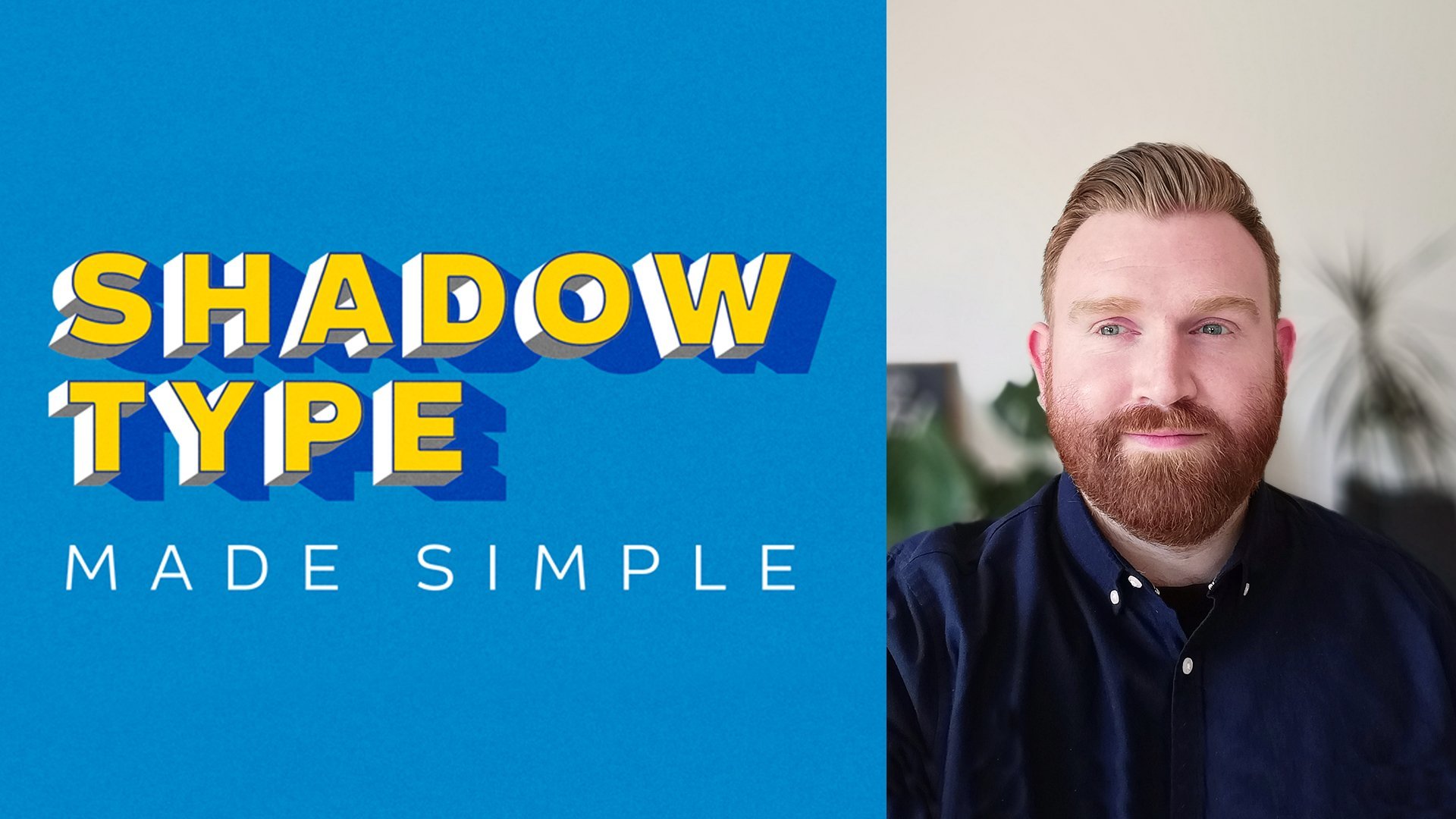
Tipografía con sombra en Adobe Illustrator simplificada
Introducción
Cómo hacer ideas en miniatura
Cómo seleccionar una paleta de colores de masal
Fuente de sombra y luz
Crear tipo de 3D
¿Dónde estamos ahora?
Retoques finales
Crea una pieza de lettering en 3D de tu cita favorita.
Una descripción del proyecto de clase:
• Trucos para hacer el dibujo y el diseño de tipografía fácil
• ¿Cómo se nail la selección de tipo?
• Aprende a crear un impacto con el color
• ¿Cómo elegir las mejores combinaciones de tipo?
• ¿Cómo añadir profundidad y interés a tu trabajo?
• ¿Qué son esos toques finales que hacen un zing?
1. Introducción: Hola, Mi nombre es Russell. Soy diseñadora freelance. Trabajo en Londres y alrededores para clientes grandes y pequeños. Tengo casi 10 años de experiencia trabajando en una variedad de proyectos que van desde cualquier cosa como palabra de identidad de marca hasta conferencias personalizadas para marcas de gran nombre. Durante este tiempo, no tengo que trabajar de manera eficiente e inteligente a Craig. Qué espantoso llamativo. A lo largo de esta clase, mis consejos de profesor tienen que puntar en promedio laico. Es como golpear lo horribles que las paletas de colores clavan esas combinaciones de tipos y cómo agregar a la deuda a tu trabajo. Bueno, entonces generalmente habilidades para crear tu propio impacto, por favor. Este pasado implica colección La habilidad se puede aplicar fácilmente a otras áreas de diseño o conferencia desde cualquier cosa como consejos sobre cómo diseñar conferencias. Crear sus propias pautas para financiar la selección o incluso seleccionar paleta de colores. Crean para golpear a la obra. Aprendes esos atajos de mano que puedes usar en Illustrator en photoshop al final de su corazón para poder sacar efectivamente una pieza de respuesta única de conferencia porque a partir de combinaciones sabes crear impacto. Cualquier preocupación, directorio o diseño que se le añada detalles extra. Esta clase tendrá apenas arriba tu juego, solo terminando y cruzando o qué 2. Cómo hacer ideas en miniatura: cosa muy rápida y fácil de hacer lo que tiempo. Por lo que sólo dibujamos nuestros lineamientos. No enviarlo como fondo organizado. Pero te mantendrá en un asustado no en la ciudad te salvará. Genial. Entonces te quitas las cerraduras aquí. De ninguna manera. Sabemos que nuestra palabra está colgando. De acuerdo, Punta rápida para que cualquier cosa sea re letras. Yo estaba rompiendo las ballenas en bloques visuales. Imagínese, como un número de rompecabezas que así sé que cuatro está en Hang dos es inning. Y en este cinco ahí dentro y eso solo te ayuda a planear. Aquí vas a romper 20 comentarios, trabajando en los frentes y esas cosas, ya sabes, espacios y todo lo que va a funcionar. Genial. Tomémoslo en ritmos realmente rápidos. A lo mejor algo en ángulo nos va a funcionar. Para que conozcas estas las que queremos destacar y en va a haber un sub minúsculo poco en algún lugar ahí. Tres noches que eso es en términos de prudencia pueden ser una, dos y tres. Vamos a tomarlo. Tal vez un competidor en un ángulo de Gricar's y hang podría estar disparando a través de la página en Podría estar en unos círculos pequeños y ellos y sus podrían seguir ese yendo a la derecha Teoh ángulo. Todo así se va a enderezar. Está bien, genial. A lo mejor eso es intentarlo. Me pregunto un truco de ángulo. Está pasando por el tablero Delgadez o lo que vemos en esa forma los ángulos siguen siendo los mismos marcos. Y simplemente no lo hicimos muy rápido y quedándonos en la ciudad. Sí, encantadora. Entonces sabemos entonces que fueron sombras. Podría ser que esta es una bonita sección transversal hay cosas diferentes pasando. Y te imaginas las sombras a tu cruz derecha diciendo, Eso es lindo. Tienes a mi serpiente al espacio lleno de pareja que le decimos antecedentes que sería una especie de convertirse en una Ya sabes lo que realmente está mal? Tan solo llévala a la siguiente etapa. Nosotros solo un poco más de lápiz labial en ella. Eres bueno. Y esto pensar a través de los chicos que hacen es un poco más agradable porque trabajo en los ángulos. Pero estabas en el distrito. Llévame a ver No. Entonces voy mano tensando que habrá fuera escaleras tipo de edad una vez un marciano dentro ahí. Por lo que probablemente se sentará en cualquier dispositivo que utilicemos para que diga realmente agradable manera rápida, fácil tus ideas sobre la edad, olvidando gallinero en lápices en fotos, lápices cortos en Australia, colores formas. Si auto idea realmente limpia llena de artesanía en Charles, es una muy bonita y esto acaba de finalizarse lo que ponemos en página. Después llevamos esto a las televisiones al instructor. Miramos los fondos y vemos qué podemos tomar en cuanto a que son. Creo que esto es realmente, bueno, genial. 3. Cómo seleccionar una paleta de colores de masal: El paleta de colores es una de las partes más importantes de un diseño que le crea que eres capaz de escoger un combo de colores que realmente, realmente aparece. Tu objetivo principal es crear contraste en tu paladar y pieza de trabajo. opuestos claros y oscuros y de color en la rueda de color son tus mejores apuestas por igual. Los colores de Mood boarding realmente pueden obtener tu inspiración. Gary. A partir de esto puedes dejar caer los colores y empezar a crear un impacto realmente conceptual para la paleta de colores. De acuerdo, entonces, ¿dónde encuentras el color? Hay algunos grandes recursos alrededor, y creo que como diseñadora, realmente deberías estar esforzándome con materiales impresos. Este es un gran tipo de sombra de libro. Es brisa Filadelfia y Stephen. Helen es una gran colección fuera de tipo increíble de todo el mundo que personalmente y juntan. Te viniste sitios como ceniza virgen. Es muy bueno para inspirar paletas de colores, y realmente podrías sacar de las imágenes usando que lo dejo caer o para ti y lo llevo Illustrator o Photoshopped para hablar realmente genial. Imágenes de Teoh para tableros de humor Bendice. Mira ahora en un así vamos a través de la página para adobe color. puedes ver que tienes diferentes opciones para ir por las que pasamos ahora, tonos compuestos complementarios y personalizados, y es una gran herramienta en. ¿ Acabas de arrastrar por ahí? Este círculo aquí solo para jugar y seleccionar los colores de las joyas es realmente es de extremo abierto. Ahí tienes los colores hexagonales, lo cual es increíble de sacar. Puedes individualmente, bebé lo enorme de cada color que puedes establecer diferentes colores es de colores basados, lo cual es increíble hasta que quieres una base alrededor del auto y comienzas a probar nuestro monocromático que incluso puedes explorar. Y aquí es donde el color de Adobe realmente entra en el suyo. La gente no puede volar las paletas de colores, y automáticamente dice: ¿Es a partir de imágenes que se están subiendo? Y es una forma tan inspiradora de dibujar color de una comunidad incluso puede ver tendencias, y donde eso está alineado en la moda o diseño gráfico o ilustración. Es increíble ver cómo la gente está usando colores en diferentes industrias. Probablemente airearía del lado de la precaución con esto, y usted sólo utiliza su inspiración, explorar y crear van a estar donde realmente se puede cultura y crear esas paletas de colores allí fuertes en su trabajo. Aún mejor, aquí tienes opciones para sacar los colores en RGB c m y que HSV o lab, que es una herramienta tan asombrosa para tener al alcance de tus dedos. Por lo que recomendaría que los mares Aquí es donde deberías estar creando tu llamada al respecto porque es tan poderosa, tan fuerte. De acuerdo, ver que en este ejemplo, se puede ver que he sacado el tipo de la imagen del título para este auto encendido. He sacado los colores que utilicé en cada elemento individual, y ahí hay seis colores que van desde el fondo hasta los contornos de las sombras hasta los reflejos. El semáforo bajo. Se puede ver que he resaltado cada área y cada color diferente que he usado en una pieza de trabajo. Ahora pasemos al siguiente bit donde los he sacado en apenas una paleta de colores plana en círculos, solo para que veas el gran contraste en colores. Tienes tres tipos de blues, un color realmente fuerte, vibrante, un bonito cumplido, tu producto al blues para las sombras. A mí me gusta mucho destacar, y eso sólo va a escoger. ¿ En qué forma ayuda realmente? Gran impacto en tus letras. Esto se puede ver en nuestro siguiente bit, donde el tipo explota y se puede ver cómo se está componiendo esto en capas siempre diferentes . Y se puede ver cómo esos colores aquí realmente trabajan juntos para crear ese impacto para la paz de la letra sobre cuándo volverán juntos. Se puede ver que realmente conduce a casa la forma, la forma y cómo realmente funciona esa sombra. Difícil hacer que esta redacción realmente destaque. Forma de empezar con nuestros colores de seleccionados una bonita paleta de colores. Aquí puedes ver que hay un amplio plebeyos de despedida que tenemos apoyando verdes rojos de apoyo y realmente bonito color claro resaltado, lo cual es genial cuando les damos esperanza. Estos los greens y el meñique enorme están lo suficientemente lejos el uno del otro que van a bajar, lo cual es perfecto. Diga una nota rápida sobre el manejo del color. Y tal vez quieras seleccionar todo en uso, deshacerte de todo o de estos porque eso ha nacido. Entonces quieres agarrar que un selectivo lo bebió en ese seleccionado Arrástrelo en el mismo otra vez en esto es solo una ayuda realmente te maneja, Carlos, que nada va a estropear y quieres pasar y resbalarlos como globales. Ver, en lo que eso va a hacer es, um, Tesis dirá tu tocino en cualquier mal día. Cualquier color de cliente cambia cualquier último minuto se enmienda a los colores o decir tal vez necesitaban obras de arte en una hora, cualquier cosa por el estilo. Esto significará que debido a que es global, cambias las joyas de color en una vista previa, y cambiará en la cosa. Por lo que sólo hay que recordar que estos ahora están establecidos como thes colors se significa ahora que quieres sólo los colores. Estás bastante feliz. Tenemos el matiz o algo así. Simplemente puedes ajustarlo y ver lo rápido que fue eso. Qué asombrosamente rápido. Por lo que puedes cambiarlo para mentir Nombres azules regenerativos los oscuros. Puedes cambiarlo para ver em como un realmente es interminable en tu guardar. Tanto tiempo y esfuerzo acabamos de agilizar acciones inteligentes como esta siempre va a ahorrar mejor tiempo. Por lo que es genial tener esta licencia obvia para esos tiempos en los que sí consigues esos cambios de último minuto. Permanece su último minuto. Todos sabemos que sucede que esto te detendría poner en ese año. Por lo tanto, una forma realmente buena y práctica de controlar los colores y gestionar dentro del panel de muestreos utilizando herramientas globales en Adobe Illustrator. 4. Fuente de sombra y luz: legible ilumina a alguien que si no lo consigues del todo bien, destaca aquí. Se puede ver que he mostrado la fuente de luz para su pieza tipográfica desde las cartillas de título . Necesitas imaginar la luz que brilla hacia abajo desde la parte superior izquierda viniendo a través. Ponte al frente del tipo y rebotando, echando una sombra a los derechos del tipo. Imaginar el tipo como un objeto viviente estructural, respiratorio realmente ayuda a la hora de planear el sombreado en el color. En esta próxima luz, se pueden ver tres fuentes de luz y tres letras y cómo todas tienen efecto de manera diferente. Se puede utilizar esto como referencia. Cuando no lo afeité a tu pieza, podrás encontrar esto en la sección de recursos para su clase. Al pensar de dónde vendrá la fuente de luz, necesitas que Teoh también piense en qué ángulo se mostrará la profundidad. Se puede ver aquí que está usando el ángulo equivocado en la deuda equivocada en el ángulo de luz equivocado . Fuente no hace que el tipo pop o destaque Aquí. Se pueden ver tres ejemplos de tres fuentes de luz, pero también el ángulo sobre la muerte. Creo que este es un ejemplo realmente bueno del que se puede sacar porque se puede ver la fuente de luz no es la única parte en el espíritu del rompecabezas para el tipo de sombra. También es el ángulo que estás poniendo la profundidad de las letras que realmente puedes ver aquí. Esta es la mejor manera de hacerlo, porque si vas a hacer conferencias desde arriba, vas a ser tonta tener la profundidad,ya sabes, en un ángulo de refighting, porque de esta manera pones todo el foco en mensaje que será del tipo. 5. Crear tipo de 3D: tenemos nuestra divertida televisión que he presentado. ¿ God paletas de color nuestra justo para referencia Arriba allá en tenemos nuestro boceto en la parte superior izquierda del lado. Eso sería realmente útil, sólo de referencia de retroceso para alguna vez atascarse. Ahora la diversión que he usado una combinación de tamaño es que realmente conduces. El impacto es importante. ¿ Recuerdas cuando mirábamos el fondo clavando? Ya hemos elaborado la jerarquía del tipo. Esto es un papel enorme en jugar y recoger con los fondos, porque esto es realmente importante para impulsar el impacto. Se desea que el más alto en la jerarquía, escriba los fondos. Teoh ser mucho más grande, mucho más bullicioso, realmente flamboyante en sus palabras secundarias como un off si mucho más pequeño Andi en un frente de perfil muy bajo . Es así como manejas la mayor cantidad de impacto. Financiamos la selección como a quién enviamos aquí nuestros lineamientos, los configuramos en amarillo y nos sentamos suficiente tipo aquí con una gran cantidad de seguimiento. Y puedes hacer esto con Opción Flecha en cualquier dirección. Si seleccionas toda la palabra en esto solo ampliará la pista por ti. Vamos a tomar las palabras. Siempre una copia. Ten siempre una copia de tipo vivo en el lado derecho del tablero de arte. si acaso lo necesitas. Voy a esbozarlo en. Vamos a compartirlo en, transformarlo para encajar para que coincida, como nuestro boceto aquí en las pautas. No va a usar la herramienta de mezcla presionando comando de opción be. Verás el fondo a la izquierda ahí, Mikey ataca. Y esa es una copa muy rápida, muy corta. Y luego solo vas a hacer doble clic cuando la herramienta de mezcla y sacar las opciones de mezcla . Vamos a usar pasos especificados. Ponga eso alrededor de 300. Simplemente queremos lo suficiente para que se mezcle en un solo bloque sólido ahí y se puede ver muy rápidamente . Hemos creado un efecto tres d. Ahora, tómate un poco de tiempo aquí. Sólo una obra. Cómo el ángulo recto y todo así. Apenas con esta sombra, porque eso sería importante más adelante, cuanto más difícil será, lejos nos llevemos, haciendo esos grandes cambios. Así que decide ahora sobre tu tobillo de las sombras y hazlo antes más fácil usando la herramienta de mezcla , puedes mezclar objetos para crear y distribuir formas uniformemente entre dos objetos. También se puede culpar entre dos caminos abiertos para crear una transición suave entre objetos eran. Incluso puedes combinar mezclas de colores y objetos para crear transiciones de color con la forma de un objeto en particular. Se trata de una herramienta muy práctica, y una vez que te la cuelgues, eso podría usarse mucho en tu diseño del día a día ya que ahorra una increíble cantidad de tiempo. Recuerda siempre usar capas en tu documento en ilustrador estos días tiempo y te permite flexibilidad cuando trabajas con complicadas piezas de trabajo. Vamos a configurar aquí las pautas en una capa separada en amarillo, Andreas arriba otra capa para trabajar en agregar en tu diseño. De esta forma, siempre podrás hablar a lo largo de la capa directriz. Si bien hablamos de jugadores, serás la persona más popular en su edición de estudio de diseño. Etiquete correctamente sus archivos en capas. Deja una buena impresión duradera, y poder seleccionar exactamente la capa correcta en el momento adecuado en última instancia te da un flujo de trabajo mucho más limpio. He trabajado muchos lugares cuando se hereda el archivo de antiguos diseñadores y hay 1000 o 100 capas. Ninguno de ellos está etiquetado organizado, y simplemente realmente te ralentiza y deja una mala impresión en esa reputación de Designs. - De acuerdo , ahora vamos a sumar en la sombra más oscura sombra casi offset en el tipo tres d. Y lo vamos a hacer copiando todas nuestras palabras aquí, y vamos a derribarlo de inmediato. Teoh el fondo, las bases fuera de las letras. Si te imaginas que es una estructura muy grande, objeto estaría a los pies. Y luego vamos a utilizar la herramienta de mezcla solo para compensar esto para crear sombras offset. - De acuerdo , así que no estoy muy contento con el color fuera de la base de la misma en. Simplemente voy a pasarlo por ahí agregó el dupe de los ricos chirridos. Simplemente agrega un poco de contraste y resalta esas palabras clave que tenemos. - Tenemos nuestros objetos mezclados, e vamos, Teoh, Teoh, ampliarlos en las opciones de mezcla encendido y vamos a usar el poder. Encuentra una herramienta, Teoh, Conviértalos en un único objeto. Ahora tenemos la sombra como un objeto singular. Quiero mostrarte una manera realmente inteligente de salir añadiendo en el detalle de la sombra sin tener que dolor estación Lee doblar y pedir prestado y la sombra sobre el tipo a escuchar. Hemos creado una máscara de recorte y vamos a usar ese Teoh Ocultar la sombra ahora, ahorra tanto tiempo. Una vez que te metes en ella y empiezo a ver que se juntan, nos daremos cuenta de cuánto de una mano es esto y cuánto tiempo ahorra de ese realmente molesto, trabajo realmente molesto, detallado donde estás mintiendo, que píxeles, que a veces está bien. Pero cuando estás en una fecha límite ajustada o alguien está respirando por el cuello, esta es una forma realmente limpia de trabajar esa parada. Jura por el tocino Puedes ver aquí que estoy usando sus formas repetitivas, enredos. Ya puedes ver por qué quería tener mi sombra recta, porque en esta etapa del proceso, realmente sí ahorra tiempo y te ayuda a no estresarte por el ángulo. Fue todo así aquí sólo estoy trabajando de la mejor manera. Teoh, arriba a la derecha PC está recordando sobre las fuentes de luz de las que aprendimos antes en el curso de share escolar on y me reclaman el pentáculo ajustándolo alrededor si se colocarán los reflejos. De acuerdo, entonces estamos en un buen lugar. Ella va a mirar eso ahora. Este es un buen ejemplo. Si no íbamos a usar el último método de recorte, así aplicaríamos esas sombras. Todos esos aspectos destacados, Proceso muy fiddly. Conseguir alinear esquina a esquina es muy, muy juguetón. Un buen ejemplo al ver otra forma de que se puede lograr el mismo objetivo, pero es seis veces su corazón. Ahora vamos a sumar en los aspectos más destacados al tipo de esto transformará nuestro trabajo será realmente increíble cuando ella empiece a pasar por él y se puede ver cuánta diferencia hace. Sólo tener ese paso arriba en desarrollo es Sí, es algo más es realmente, realmente bueno. Simplemente siempre agrego algo más al trabajo. Recuerda, siempre es más fácil de quitar que el At T siempre desarrollado. Trabajamos ese poco extra. Pasa 1234 de nuestra y siempre podrás quitártela. Es mucho más sencillo, genial que estuvieras en un buen lugar. Yo soy. Hemos agregado en los aspectos más destacados. Se puede ver el impacto general que está teniendo. - Entonces ahora tenemos una paz final o las sombras configuran todos los aspectos destacados puestos. ¿ De qué otra manera ahora, podemos, tía, meternos en nuestro trabajo, estas partes extra especiales y toques finales que harán que nuestro trabajo se detenga? 6. ¿Dónde estamos ahora?: Entonces, ¿dónde estamos ahora? La próxima semana tenemos nuestro tipo. Has dispuesto con la jerarquía corrects en el sello en la miniatura a lápiz, y después hemos tomado en ilustraciones. Hemos seleccionado esos asesinos telefónicos com gestiona va a crear un enorme impacto en. Después empezamos a trabajar en nuestro color Palais, realmente aplicando esos colores en el en la paz para realmente que destaque sobre. Hemos trabajado en la herramienta de mezcla para ahorrar ese tiempo. Hemos aprendido esos consejos y trucos rápidos con el contundente Todo lo que va a salir una enorme cantidad de tiempo. Ángel. Sigamos adelante, Teoh toques finales. 7. Retoques finales: Por lo que ahora tenemos nuestra pieza final. Todas las sombras están configuradas Los aspectos más destacados de poner en ¿De qué otra manera ahora podemos sumar en remolque nuestro trabajo esos toques finales que realmente hacen que nuestro trabajo destaque? Esta es la diferencia entre una caja pieza de trabajo estándar Onda pieza destacada que realmente la hará estallar en la multitud Tip one one agregando ruido a tu pieza de trabajo Esto hace que parezca granjero o ilustrativo. La mejor forma de hacerlo es llevarla a la tienda de fotos. Si empezamos aquí, podemos crear una forma de cobertura de ruido realmente rápida Voy a crear el mismo tamaño que el lienzo Como en Illustrator, vamos a detener el color sólido, ponerlo en gris Luego subimos para filtrar, luego al ruido Entonces vamos a jugar con el ajuste de ruido. Tú lo quieres lo suficientemente fino Sólo estar a la altura de verlo pero no tan dominante que supera a toda la pieza que acabamos de exportar aquí y llévala de nuevo a ilustrador Genial! Entonces eso se coloca sus superposiciones Va a ser mejor oso con la capacidad sere unos 45 o así El objetivo es que alguien lo note, Pero no quieres que sea la parte clave del diseño. Esto es solo un toque sutil Eso elevará tu juego y elevará tu paz, haciéndolo ver realmente, realmente pulido. Vamos a tirar a través de bits y partes directamente desde el ilustrador directamente a tienda de fotos. De esta manera podremos mantener la colocación y mantenerla realmente agradable y limpia. Se puede ver aquí he jalado en los contornos en voy a añadir en un poco, si en una sombra a la parte principal de tipo crema. Ahora que eso está hecho, voy a enfatizar aún más la rotura creando una capa de color sólido fuera de gris. Y voy a quemar usando el quemado, todo añadiendo un poco más de sombra solo un poco más de sabor direccional solo para crear esos bonitos contrastes . Una sombra. Esto es más bien un tipo de cosa satelital, Pero realmente creo que esto sí marca la diferencia cuando se está comparando una pieza de trabajo estándar de libro con una pieza de mundo realmente se está elaborando, y eso tiene un poco de encanto real al respecto. De acuerdo, ahora solo voy a añadir unos toques finales más. Esto será un poco de una ráfaga de sol en el fondo solo para llamar la atención sobre el tipo de algunos sutil int Grady y enmascarar en el fondo otra vez haciéndolo realmente parecido profesional. Muchas gracias sacando mi clase, realmente ha sido un placer enseñársela. Ponlo juntos para ustedes chicos. Me encantaría ver tu trabajo y progresar tus bocetos de pulgar ahora así como tus proyectos terminados. Se trata tanto del proceso como de la pieza final terminada. Una última cosa en la que me gustaría dejarte puesto es que por mi experiencia, encontré que a muchos directores y clientes creativos y hasta clientes de perspectiva realmente les gusta ver cómo llegaste al trabajo de esa pieza final. A veces se sabe de esa pieza final y pulida sobre el camino que tomaste para llegar a ese creativo final. Tu trabajo hace mucho más una conexión poderosa cuando muestras cómo trabajas, cómo creas tus ideas y las pones en papel. Gracias de nuevo, chicos. No puedo esperar a ver tu trabajo en bocetos en progreso y, por supuesto, sois proyectos terminados